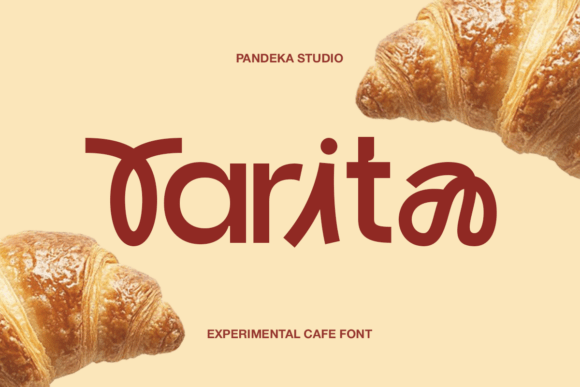
Tarita
適切なデザイン要素を見つけるのは難しい場合がありますが、Taritaは作品を即座に引き立てる優れたコレクションを提供します。
精密に作られたTaritaは、クリーンなベクター、滑らかなタイポグラフィ、そして安心のための商用ライセンスを提供します。
POD(オンデマンド印刷)製品、結婚式の招待状、またはソーシャルメディアのグラフィックを作成している場合でも、Taritaは理想的です。